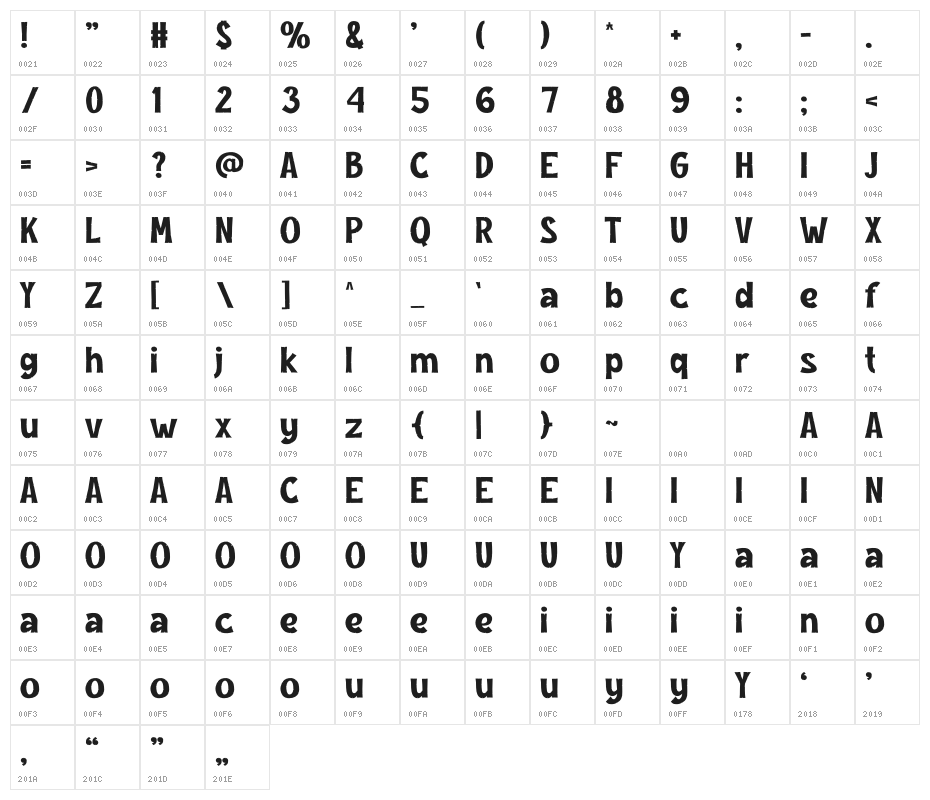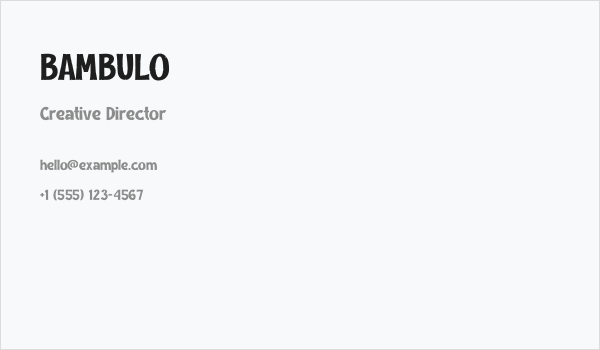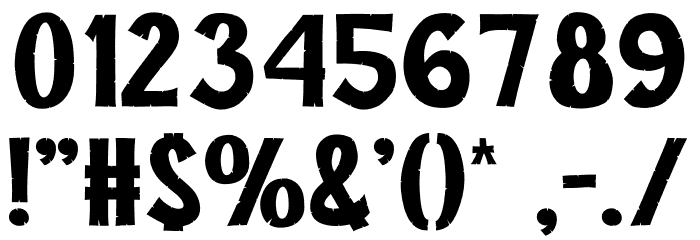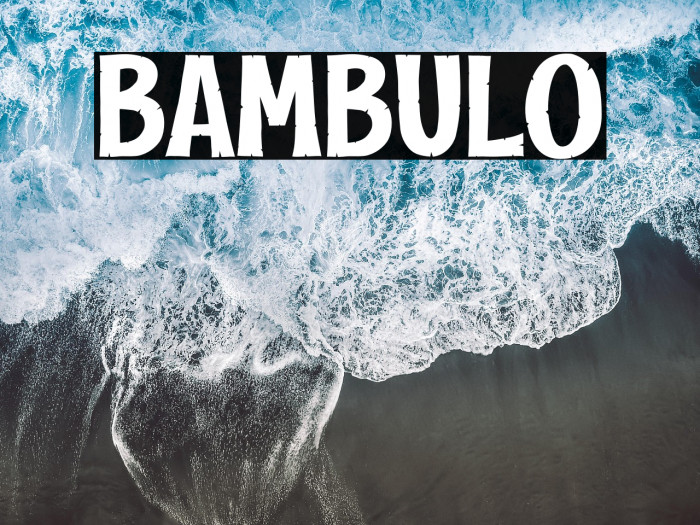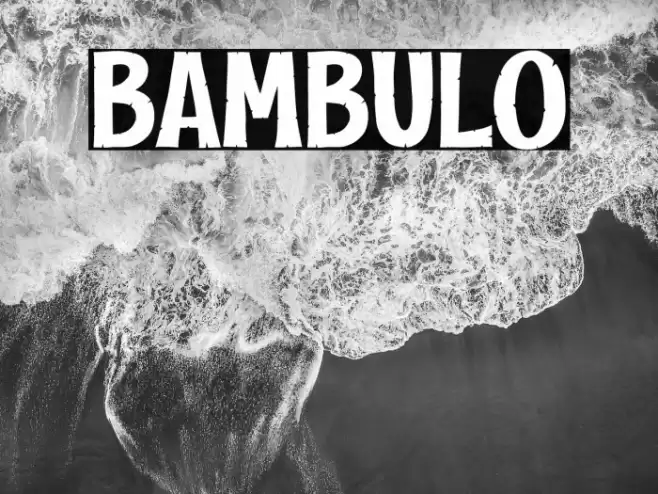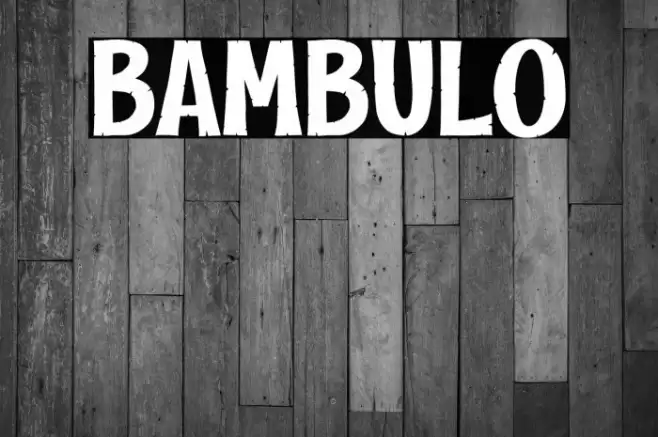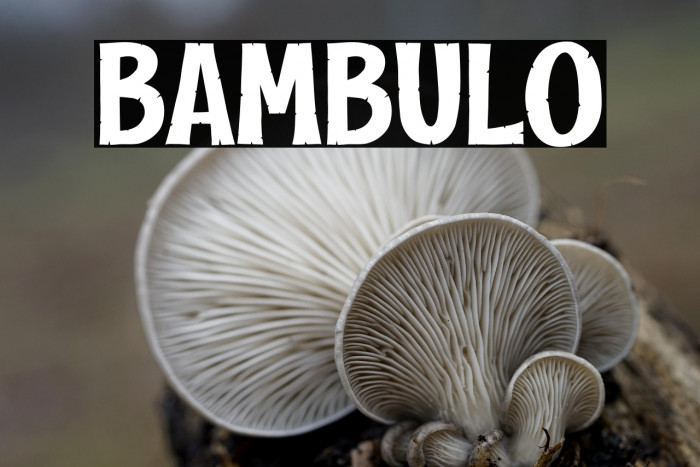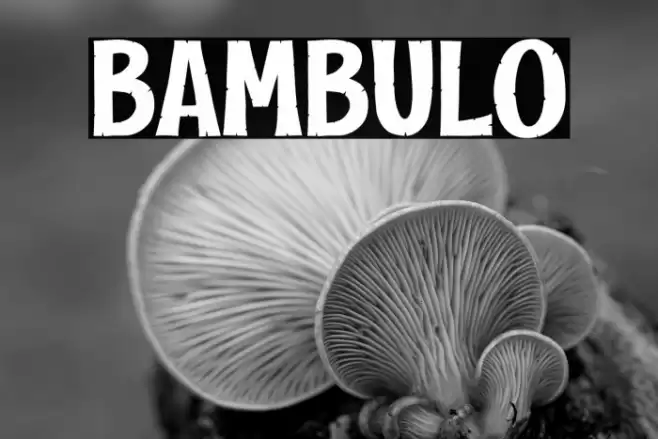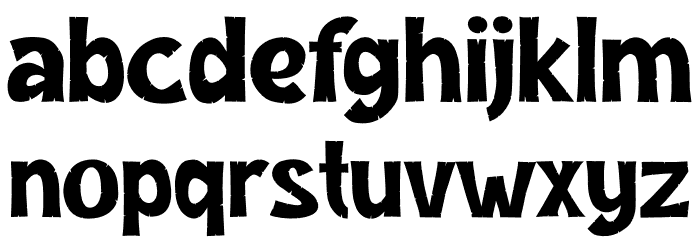
BAMBULO Font
| Style général | Playful, Hand-drawn |
| Projets proposés | Ideal for children's books, playful branding, posters, and creative social media graphics. |